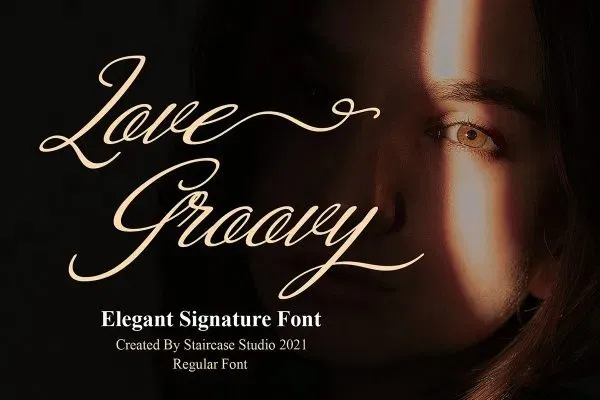
Love Groovy Font – Fonte Grátis
Love Groovy Font
A “Love Groovy Font” é uma elegante tipografia romântica feita com toques atraentes, encantadores e amorosos. Ideal para projetos que valorizam beleza e sofisticação, esta fonte vem como um conjunto de letras e números perfeitamente adaptados para qualquer necessidade de design. Perfeita tanto para logotipos quanto para identidades corporativas e criações digitais, ela também é ótima para gráficos em camisetas ou roupas, panfletos, jornais, sinais e publicidade, proporcionando um toque romântico e charmoso a qualquer projeto. Não perca esta fonte única que oferece uma pegada encantadora à sua próxima criação de design.